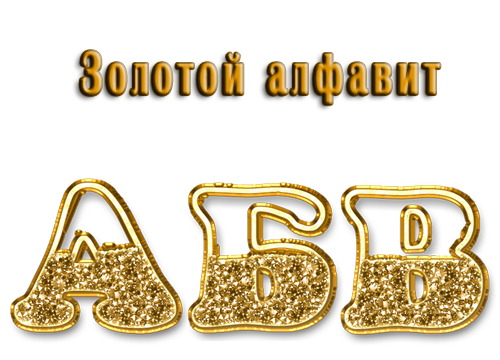
Создаём простой золотой текст в Фотошоп / Creativo.one
В этом уроке я покажу, как создать золотой текст, используя одну из полезных функций Фотошопа — стили слоя. После того, как текст будет готов, Вы сможете сохранить созданный стиль, а затем применять его каждый раз, когда понадобится сделать золотой текст.
Финальный результат:
Шаг 1. Создаем фон
Для начала, нужно создать простой фон для текста. Для этого, создайте новый документ (Файл – Новый) (File > New) (Ctrl+N). Размер документа установите тот, который нужен именно Вам (в этом уроке автор создал документ размером 1000x600px).
Созданный документ залейте темно-коричневым цветом (#211901).
Для цвета переднего плана установите желтый (#fee86a) и выберите мягкую кисть размером 500px (Brush Tool) (B). Создайте новый слой (Shift + Ctrl + N) и кистью с выбранным желтым цветом кликните один раз в центре документа.
Шаг 2. Добавляем текст
Для того, чтобы написать текст, воспользуйтесь инструментом Текст (Horizontal Type Tool) (T). В этом уроке использован шрифт Times Bold с размером 200px, цвет текста черный. Шрифт Вы можете выбрать здесь.
Теперь будем добавлять к тексту стили слоя, чтобы сделать его золотым.
Шаг 3. Добавляем стиль слоя Наложение градиента
К слою с текстом добавьте стиль слоя Наложение градиента
Результат:
Шаг 4. Добавляем стиль слоя Наложение цвета
Теперь добавьте к слою с текстом стиль Наложение цвета (Color Overlay):
Результат:
Шаг 5.
Добавляем стиль слоя Тиснение
Для того, чтобы добавить к тексту глубины, примените к нему стиль слоя Тиснение (Bevel and Emboss):
Результат:
Шаг 6. Добавляем стиль слоя Внутренняя тень
К слою с текстом добавьте стиль Внутренняя тень (Inner Shadow):
Результат:
Шаг 7. Добавляем стиль слоя Обводка
Результат:
Шаг 8. Добавляем стиль слоя Тень
К слою с текстом добавьте стиль Тень (Drop Shadow):
Результат:
Шаг 9. Добавляем стиль слоя Внешнее свечение
В финале, добавьте стиль слоя Внешнее свечение (Outer Glow).
Он придаст тексту больше глубины.
Шаг 10. Сохраняем созданные стили для золотого текста
При желании, Вы можете сохранить созданные стили слоя для золотого текста, для того, чтобы потом применять их на любой другой текст. Для того, чтобы сохранить стили слоя, в палитре
В появившемся диалоговом окне напишите название сохраняемого стиля, включите флажок около слова Включить стили слоя (Include Layer Effects).
Кликните ОК и теперь сохраненные Вами стили появятся в палитре
Увеличьте размер контура, чтобы заполнить пространство внутри букв. Вернитесь к параметрам структуры и перетащите ползунок размера вправо, пока не закроете пустые места внутри букв.
В моем случае этот параметр составляет 27 пикселей.
Для усиления эффекта освещения установите значение глубины на 180%. Затем найдите эффект Контур и активируйте его, щелкнув внутри флажка.
Шаг 6.Добавить Inner Glow